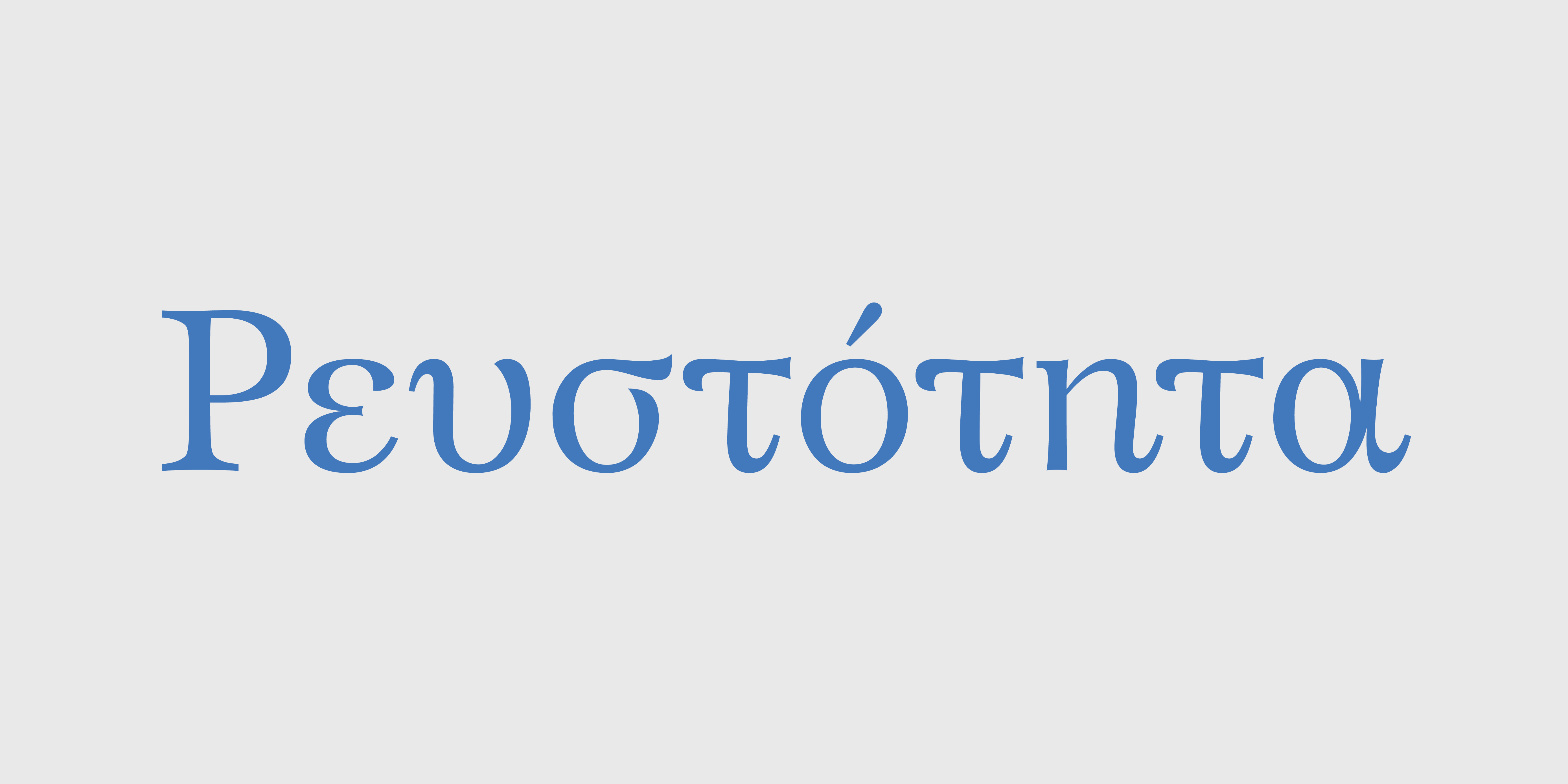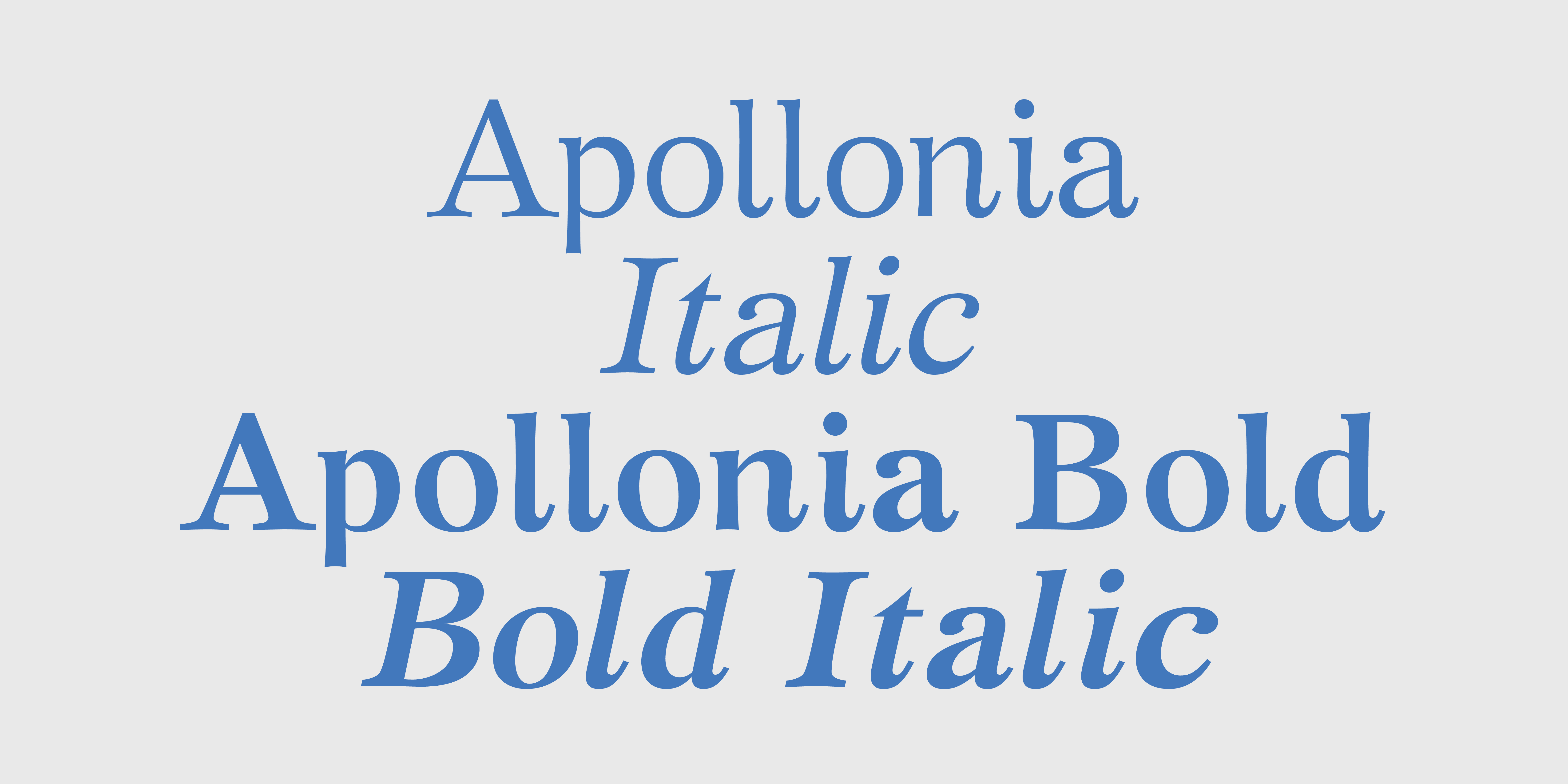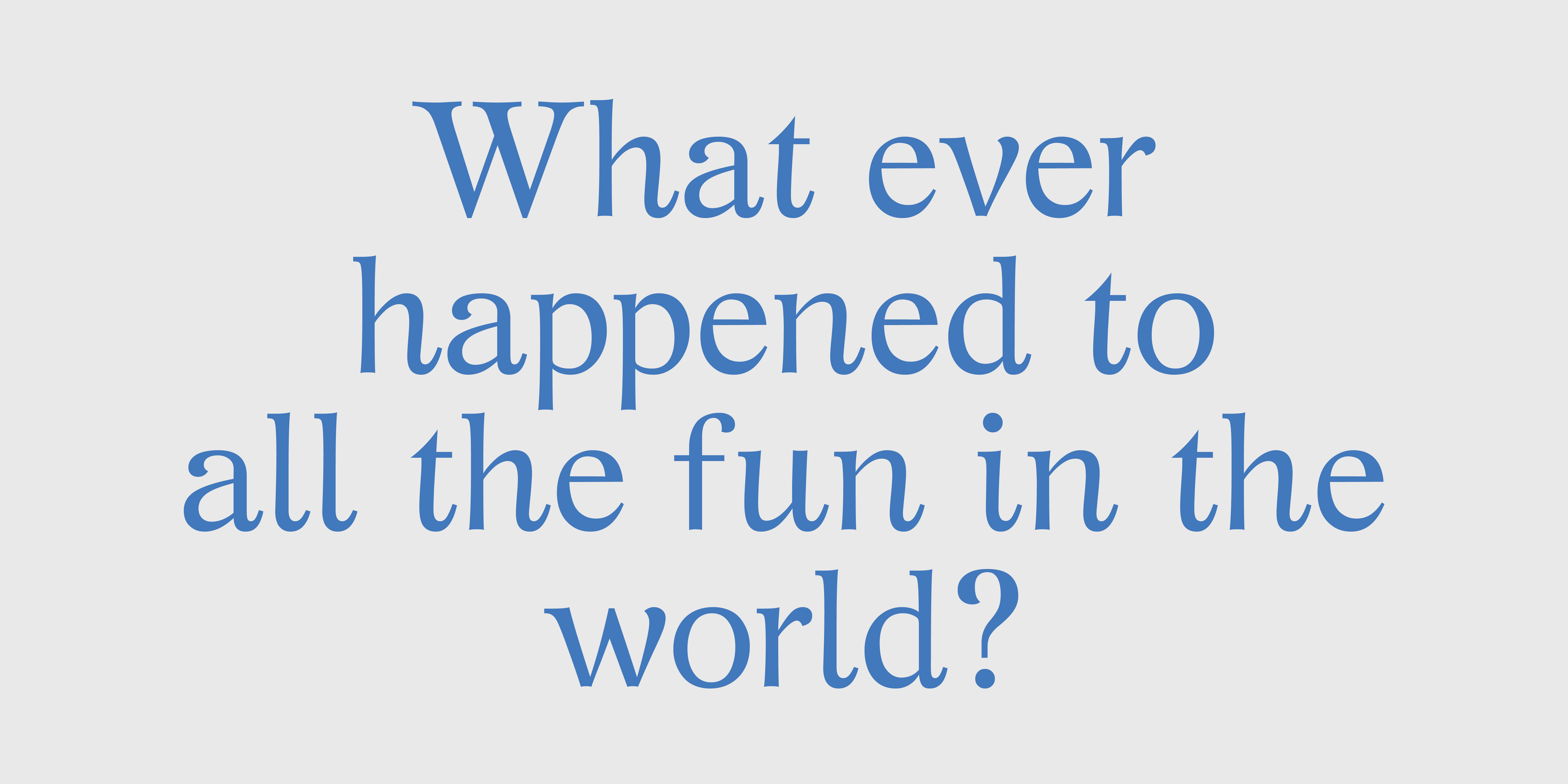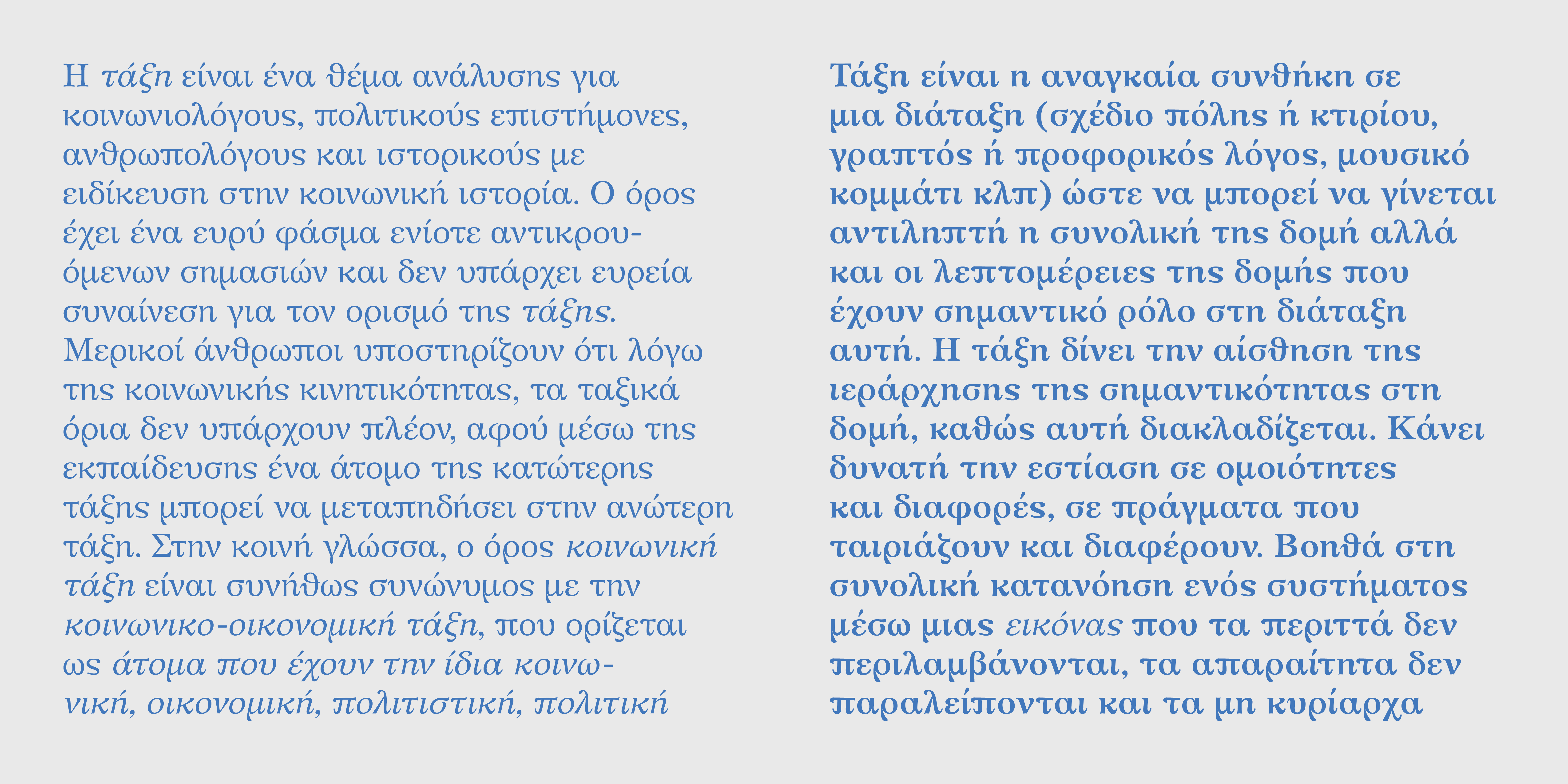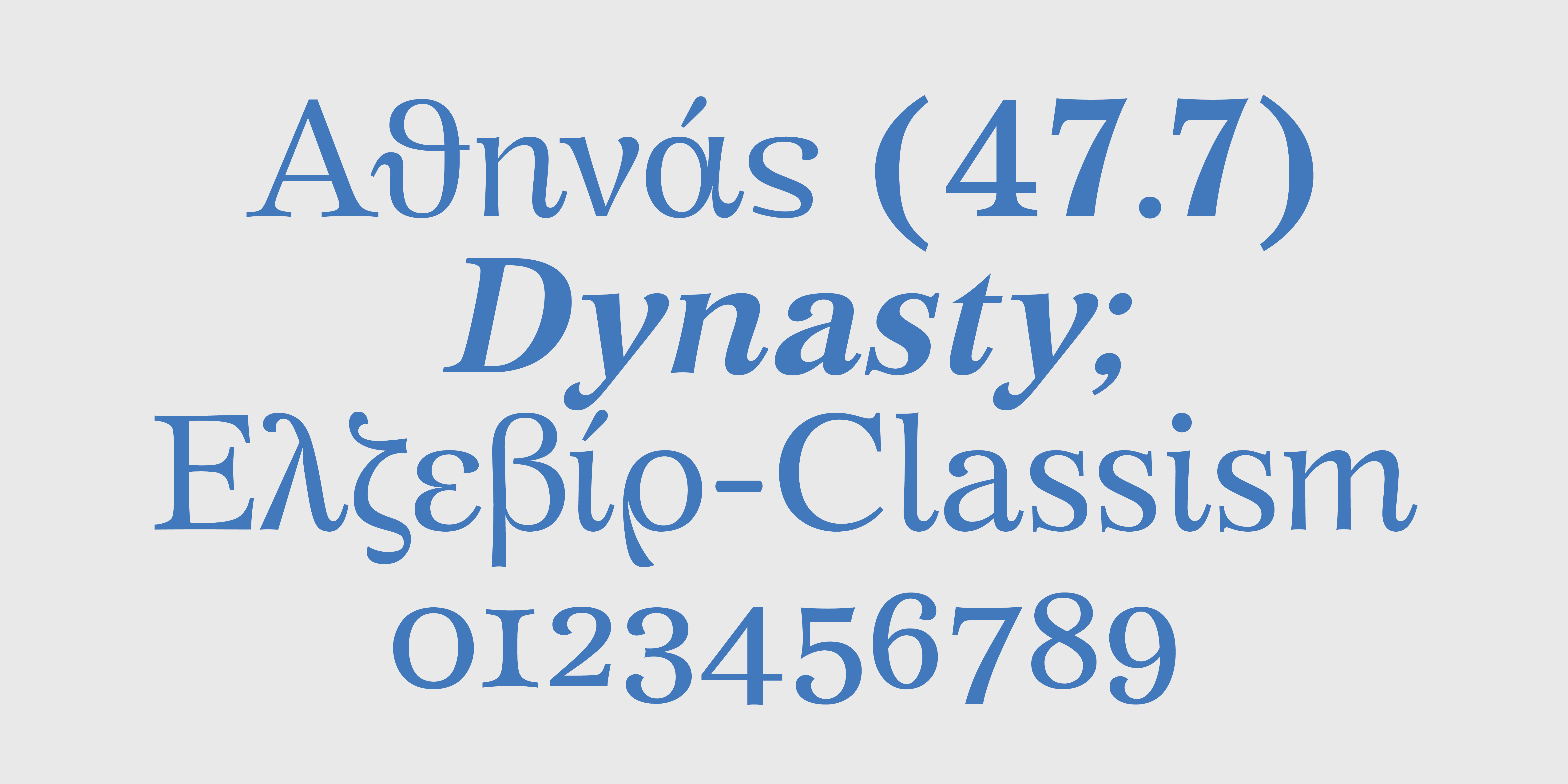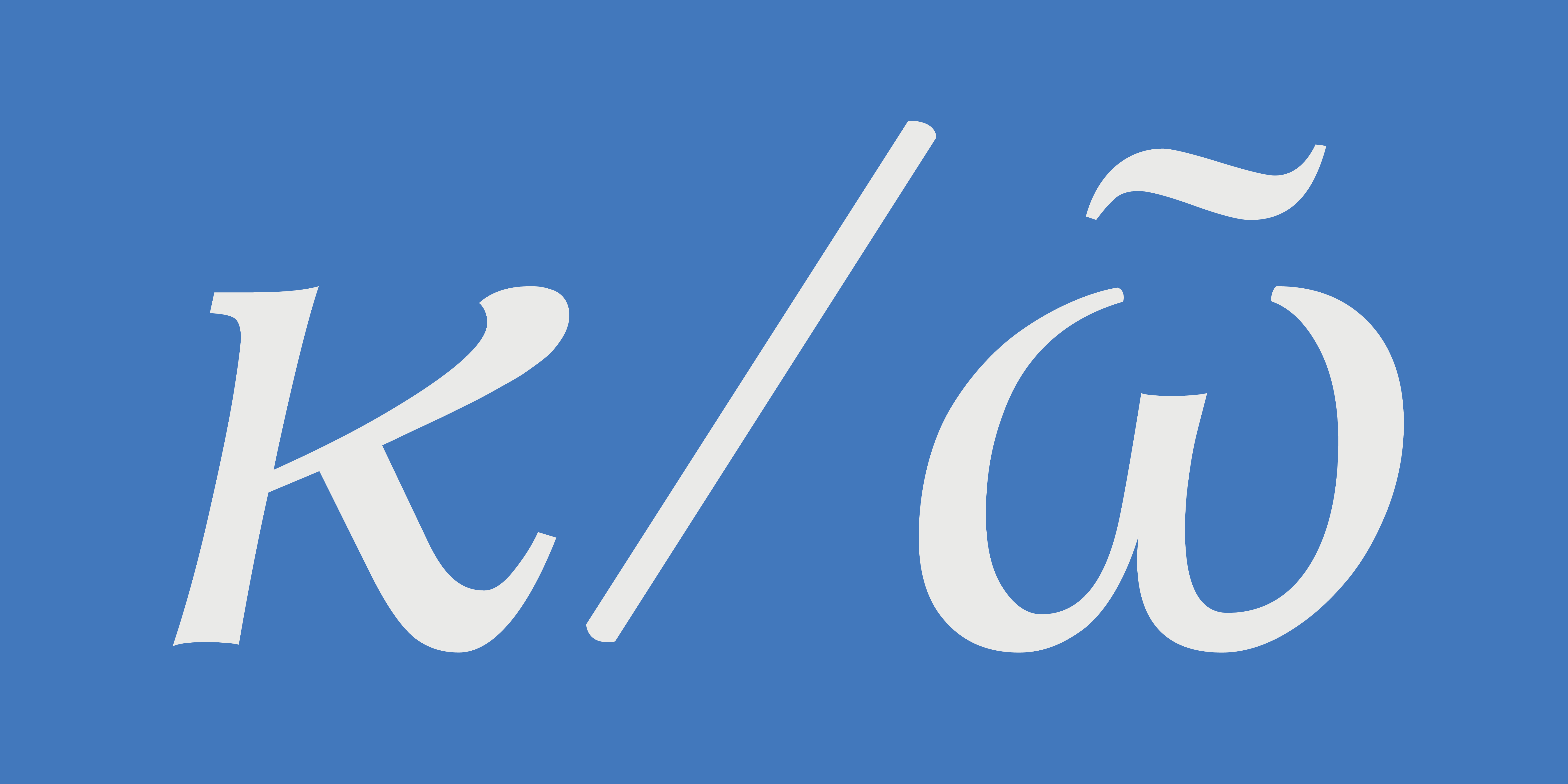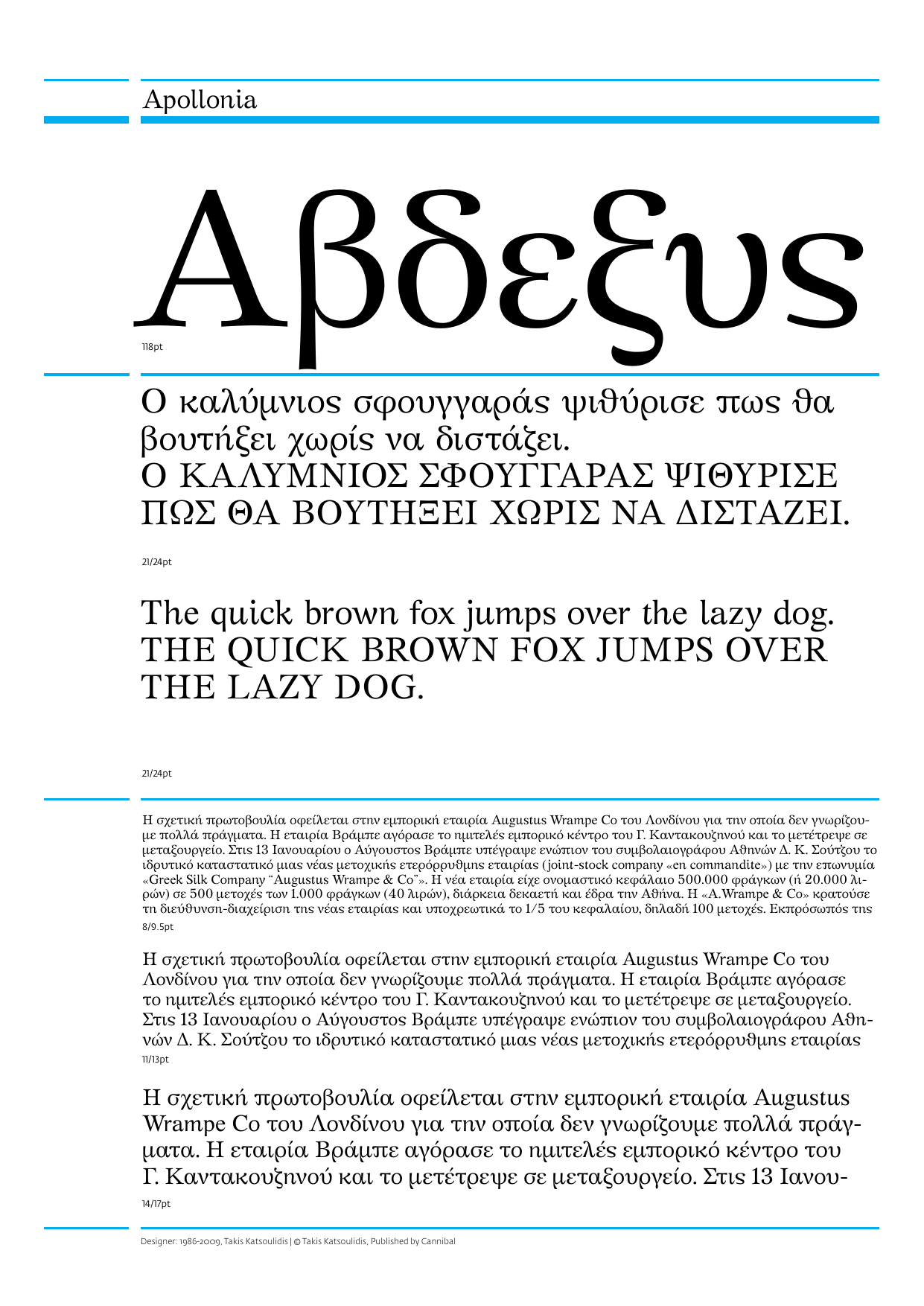
Apollonia
Πρότυπο σχεδιασμού για τα Apollonia αποτέλεσαν τα κλασικά Ελζεβίρ του τέλους του 19ου αιώνα, τα οποία δεν βελτιώθηκαν ουσιαστικά κατά τη διαδικασία της μετάβασής τους από την τυπογραφία του μετάλλου στις μηχανές της φωτοστοιχειοθεσίας. Αυτά τα Ελζεβίρ που ήταν τα καλύτερα της εποχής τους, προέρχονται από την εξελικτική πορεία της ελληνικής τυπογραφίας από τον 15ο μέχρι το τέλος του 19ου αιώνα. Η εξέλιξη αυτή είναι καταφανώς σημαντική όσον αφορά στο σχέδιο του τυπογραφικού γράμματος, αν μάλιστα ληφθεί υπόψη η αφετηρία της ελληνικής τυπογραφίας και τα πρότυπα των γραμμάτων από τα οποία ξεκίνησε. Η οικογένεια Apollonia παρουσιάστηκε μαζί με την οικογένεια Κατσουλίδης έπειτα από μελέτη που άρχισε το 1986, στα πλαίσια ερευνητικών προγραμμάτων των ΤΕΙ, η οποία μαζί με το σχεδιασμό διήρκεσε μέχρι το 1989. Η νέα έκδοση που κυκλοφορεί από το 2010 είναι επανασχεδιασμένη ενώ έχουν προστεθεί νέα σύμβολα και χαρακτήρες ώστε να υποστηρίζονται πλήρως το Western και Central European Character Set. Στη νέα έκδοση περιλαμβάνονται επίσης 4 είδη αρίθμησης (Lining, Tabular Lining, Old Style, Tabular Old Style);. (Πληροφορίες από το βιβλίο του Τάκη Κατσουλίδη, «Το σχέδιο του γράμματος»);.